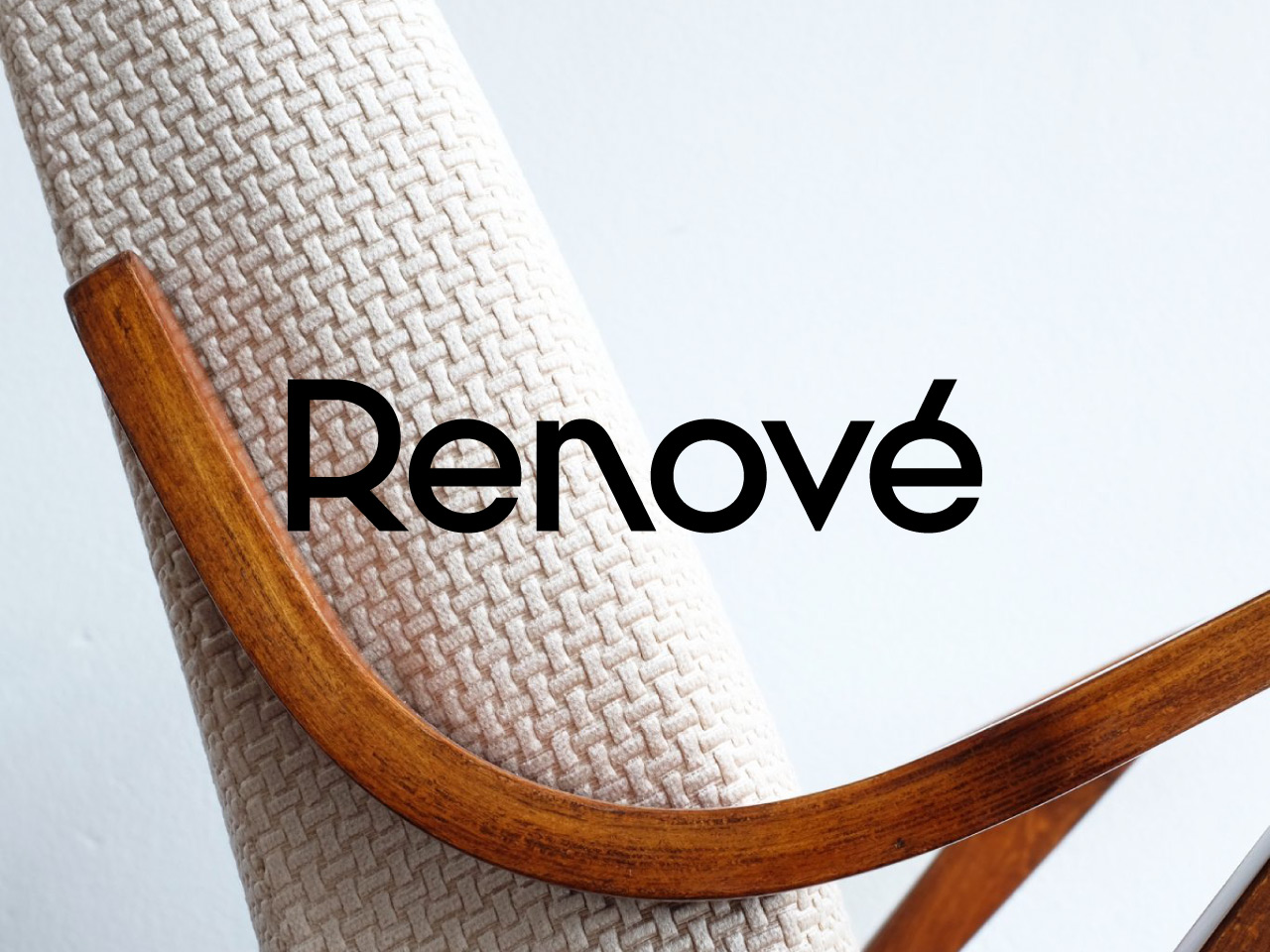
Renové
Logo pre Renové, kolektív zberateľov, reštaurátorov a predajcov modernistického nábytku a interiérových doplnkov, prevažne z bývalého Československa.
Jednoduché sans-serifové geometrické logo s originálnou konštrukciou písmena n a dĺžňom spojeným s písmenom e evokuje čistotu, modernistickú nápaditosť a estetické princípy, ktoré dominovali dizajnu tej doby.